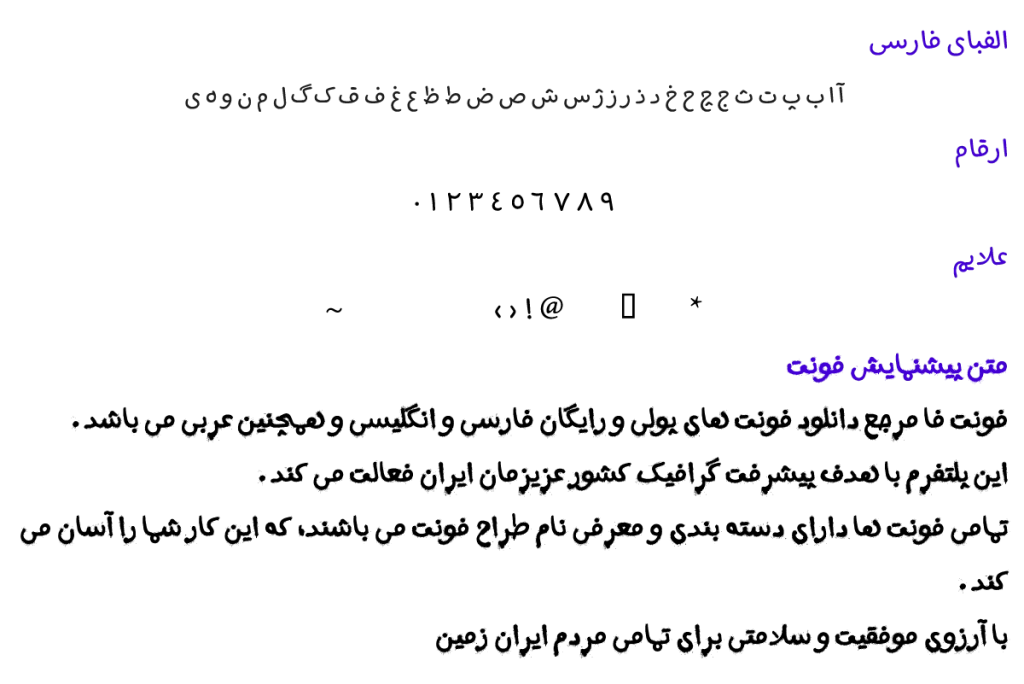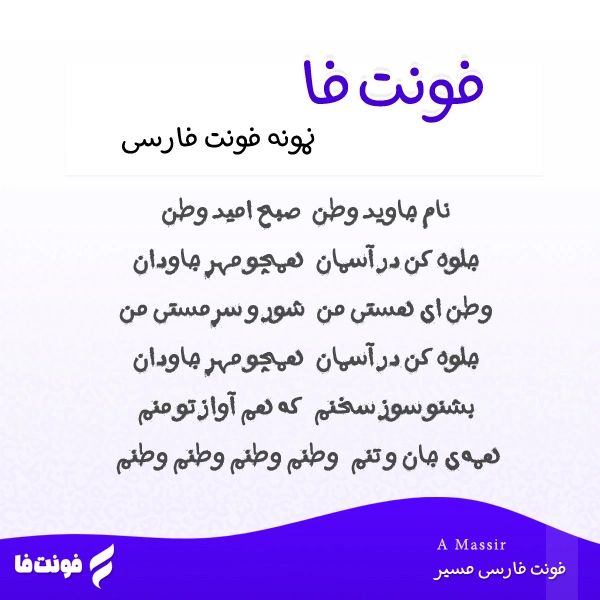
فونت فارسی مسیر – A Massir
طراح فونت: علی سواری نوع فونت: فونت گرافیکی
توضیحات و معرفی فونت مسیر
فونت فارسی مسیر ( A Massir ) از مجموعه فونت های آزاد می باشد، همینطور نوع فونت گرافیکی می باشد.
فونت زیبای مرتبط توسط علی سواری و پاسکال ذقبی در سال 1390 طراحی و ساخته شده است.
پیش نمایش این تایپ فیس را که شعر زیبای «وطن» با آن نوشته شده، در تصویر زیر مشاهده میکنید.